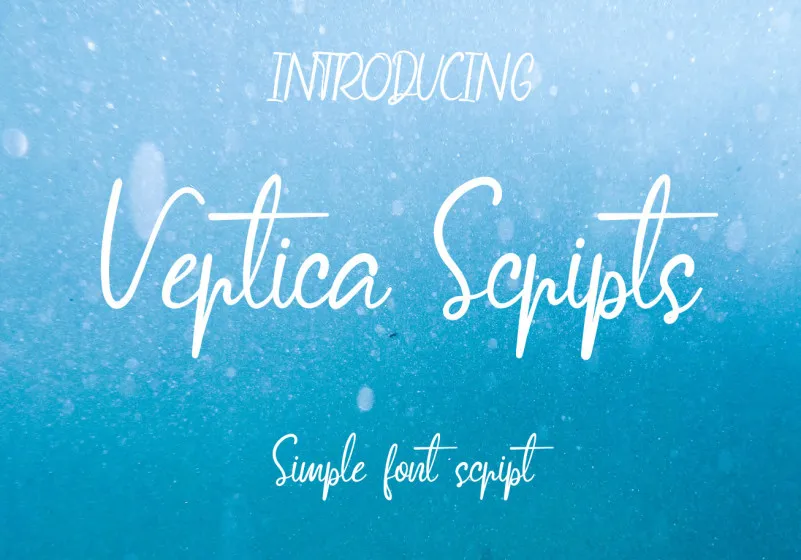
Vertica Script Font
A fonte Vertica Script é uma escolha perfeita para aqueles que buscam um equilíbrio elegante entre simplicidade e beleza. Com seu design limpo e refinado, a Vertica Script pode ser facilmente incorporada em uma variedade de projetos gráficos – seja nas etiquetas de livros com texturas delicadas, os nomes de marca modernas para sua loja online, ou até mesmo no convite de casamento mais romântico. Essa fonte é ideal para qualquer projeto que exija um toque refinado e sofisticado. Seja você um designer gráfico profissional ou uma amante da arte do design, a Vertica Script oferece tanto versatilidade quanto beleza. Com seu uso fluido na criação de texturas elegantes nas etiquetas de livros, a fonte também atende às necessidades dos criadores de conteúdo para e-books. Em um mundo digital cada vez mais conectado, a Vertica Script é uma excelente opção para os designers que buscam criar uma conexão visual entre o usuário final e seu produto ou serviço – seja através do design de logotipo devidamente concebido ou da criação de uma campanha de marketing poderosa. Não importa qual projeto estiver trabalhando, a Vertica Script oferece um toque único e sofisticado que certamente fará sua marca.